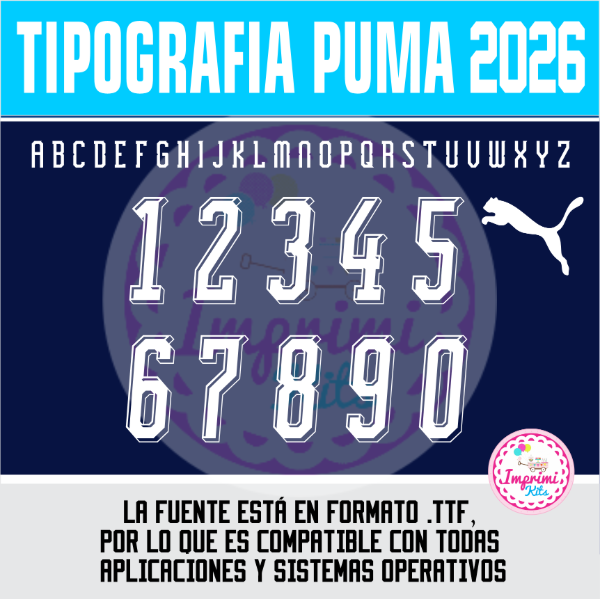
Tipografia Camiseta Ttf Otf Numeros Dorsal PUMA 2026
Tipografía utilizada por Puma para las camisetas y números de gran parte de los equipos que viste durante la temporada 2026, incluídas algunas de las selecciones nacionales que disputarán la Copa Mundial de la FIFA 2026 que se celebrará en Estados Unidos, México y Canadá.
Tipografía Números Fuente
Realizá todo tipo de creaciones con la tipografía utilizada actualmente en el club